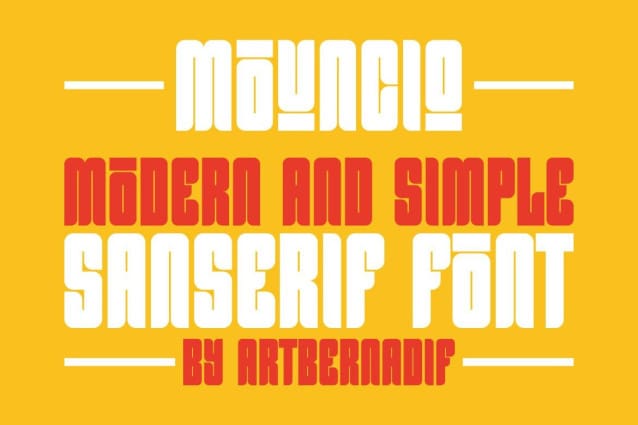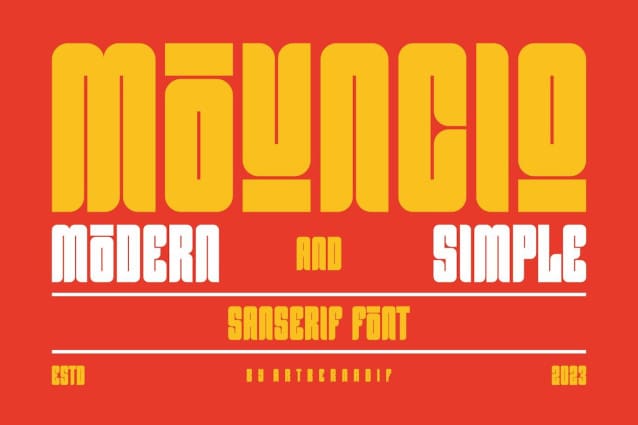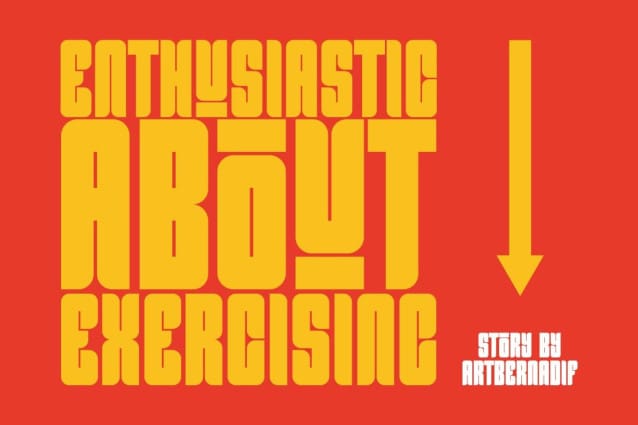
Mounciq Font
Mounciq Font – Modern Font est une police d’affichage audacieuse et authentique. La police convient à tous les projets de marque tels que le Logo, l’impression de t-shirts, l’esport, etc. Elle est exceptionnelle dans un large éventail de contextes